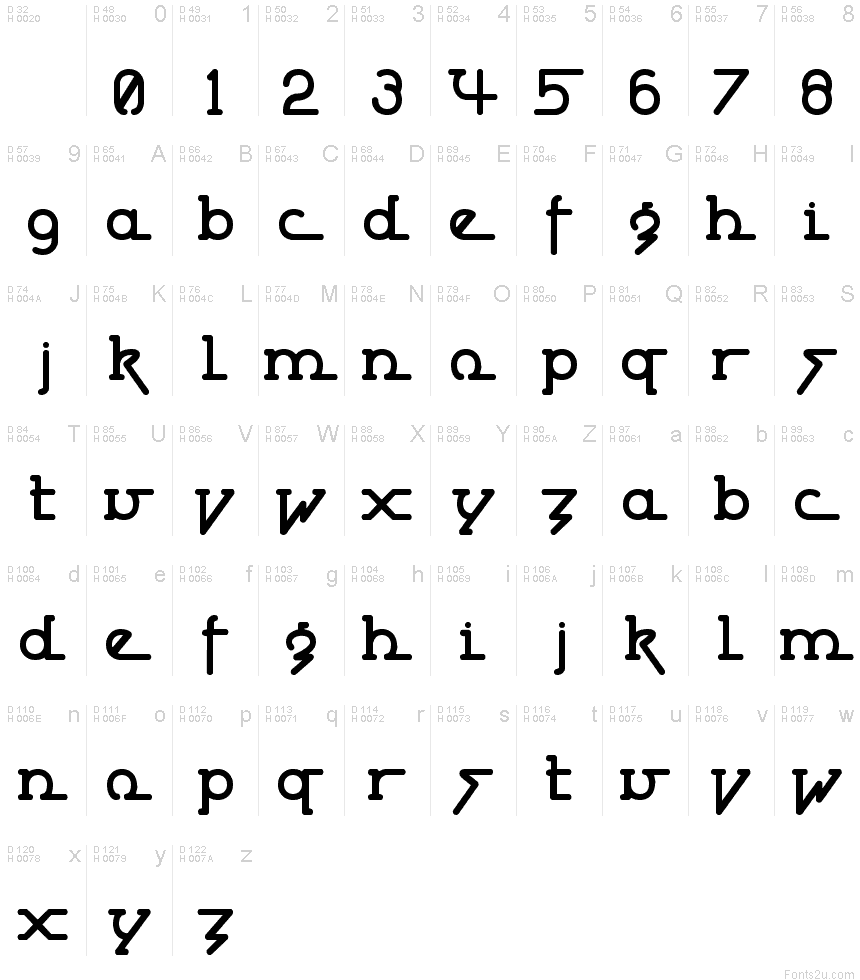
Powderworks, di ÆNIGMA Fonts, è un font display futuristico e gratuito dal look morbido e moderno. Le lettere scorrono in una linea spessa e arrotondata, mescolando forme circolari a giunzioni nette e direzionali: l'alfabeto evoca sia la segnaletica dell'era spaziale che la grafica pop di fine anni '60.
È perfetta per packaging musicali, titoli di poster, concept di loghi, flyer per club e cover, dove un font gratuito può definire l'intero stile. Usalo per parole brevi o titoli sovrapposti, specialmente se cerchi quel lungo flusso orizzontale e qualche curva inaspettata per dare carattere al design.
Powderworks (BRK)